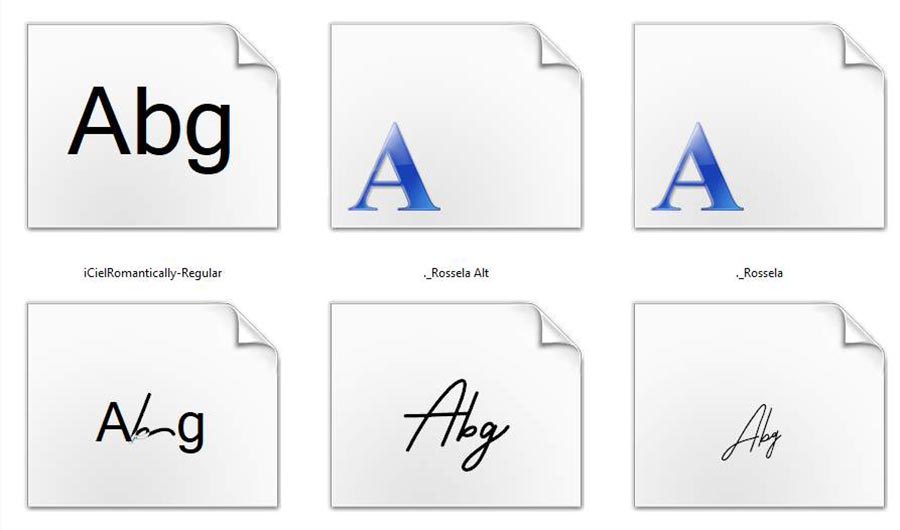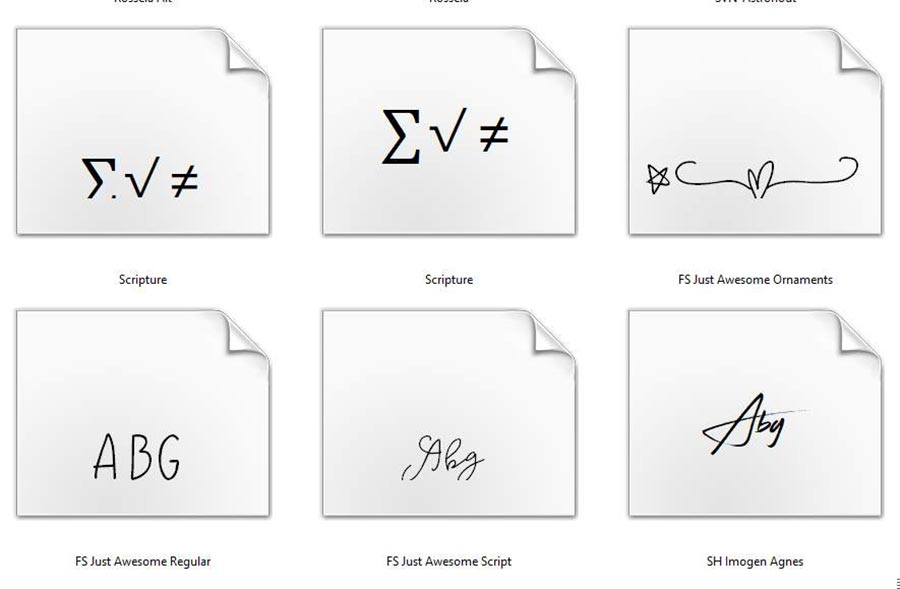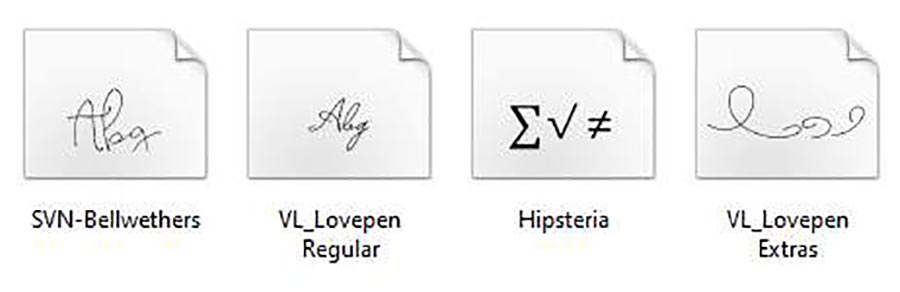
Sự xuất hiện của một chữ ký đẹp không chỉ giúp nâng cao tính thẩm mỹ mà còn tạo dấu ấn riêng biệt cho từng thiết kế. Nếu bạn đang tìm kiếm bộ font chữ ký ấn tượng, miễn phí và dễ dàng tải về, SaDesign.vn sẽ là điểm đến lý tưởng.
1. Tại sao nên sử dụng font chữ ký trong thiết kế?
Font chữ ký được thiết kế để mô phỏng chữ viết tay mềm mại, tự nhiên, mang lại cảm giác cá nhân hóa cao. Dưới đây là những lý do bạn nên chọn font chữ ký cho các dự án của mình:
• Tạo phong cách riêng biệt: Font chữ ký thường mang phong cách nghệ thuật, giúp tạo điểm nhấn và gây ấn tượng với người xem.
• Thích hợp cho nhiều loại thiết kế: Từ danh thiếp, thiệp cưới, logo đến hình ảnh mạng xã hội, font chữ ký luôn là lựa chọn tuyệt vời.
• Tính thẩm mỹ cao: Các đường nét mềm mại, uốn lượn mang lại vẻ tinh tế và chuyên nghiệp.
2. Điểm nổi bật của bộ font chữ ký từ SaDesign.vn
SaDesign.vn đã tuyển chọn cẩn thận 10 font chữ ký đẹp nhất, phù hợp với xu hướng hiện nay. Những ưu điểm của bộ font này bao gồm:
• Đa dạng phong cách: Bộ font bao gồm nhiều phong cách từ hiện đại, thanh lịch đến cổ điển, giúp bạn thỏa sức sáng tạo.
3. Gợi ý sử dụng bộ font chữ ký
Bộ font chữ ký này có thể áp dụng vào nhiều dự án khác nhau:
• Thiết kế logo: Giúp logo của bạn trở nên nổi bật và đầy cảm xúc.
• Thiệp mời: Mang lại sự tinh tế, đặc biệt cho các dịp quan trọng.
• Chữ ký email: Tạo phong cách chuyên nghiệp và cá nhân hóa.
• Mạng xã hội: Tăng tính thẩm mỹ cho hình ảnh và nội dung.